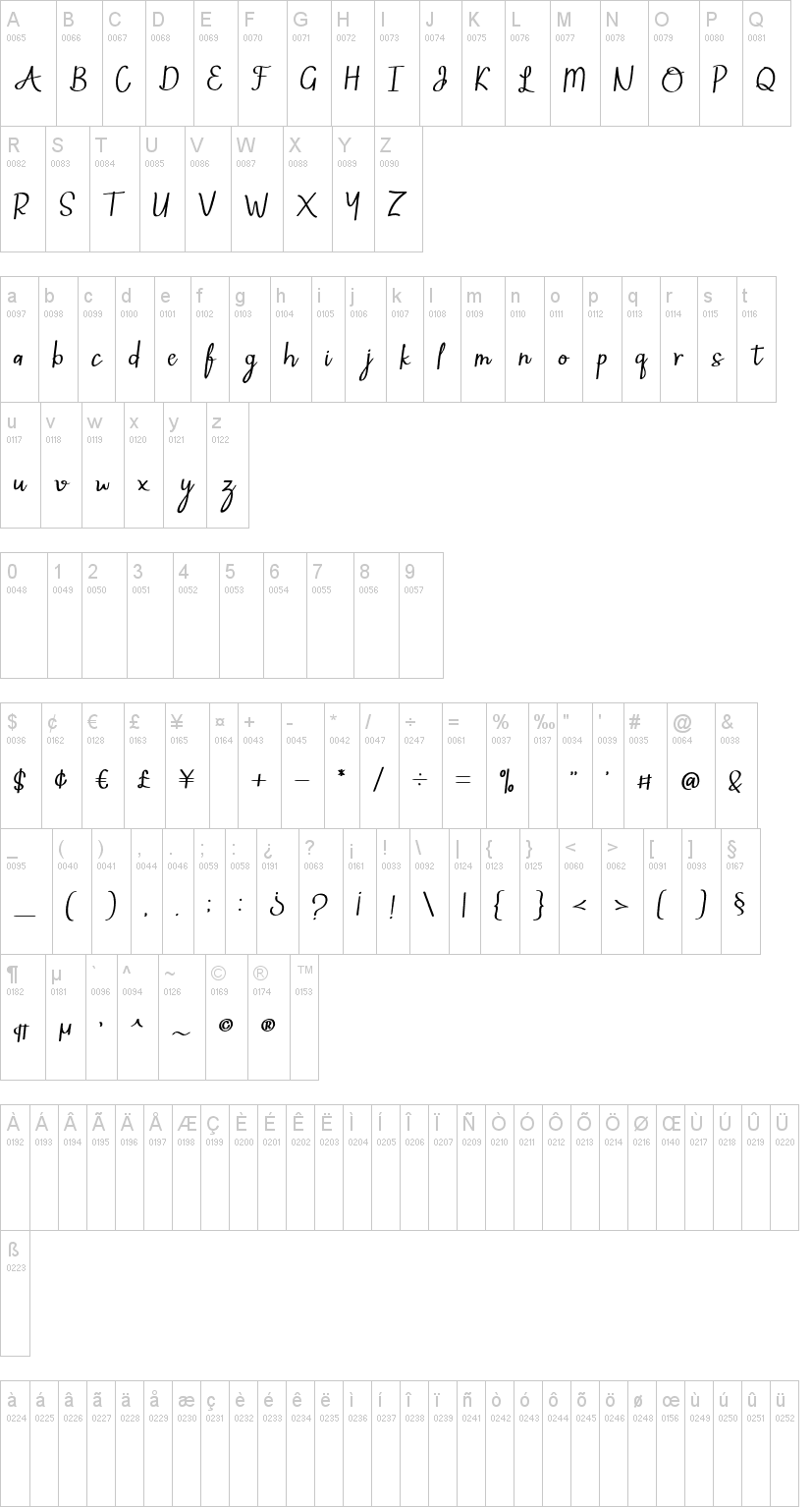
Mintlic 字体是一款简洁优雅的英文字体,它来源于一种古老的文字格式,古典的线条组合使它看起来更有深度和细节。Mintlic 字体的字母形状非常精致,具有良好的可读性,可以很好地表达出文字的意思。它适合用于各种海报、标志和宣传物料的设计,也可以用于印刷品、网页和手机应用程序的设计。内容介绍
Mintlic是一款非常不错的手写艺术字体,具有很好的视觉感,适合于文化类的宣传设计、商业类品牌的广告和产品包装设计以及个性化文字排版等较多场景。